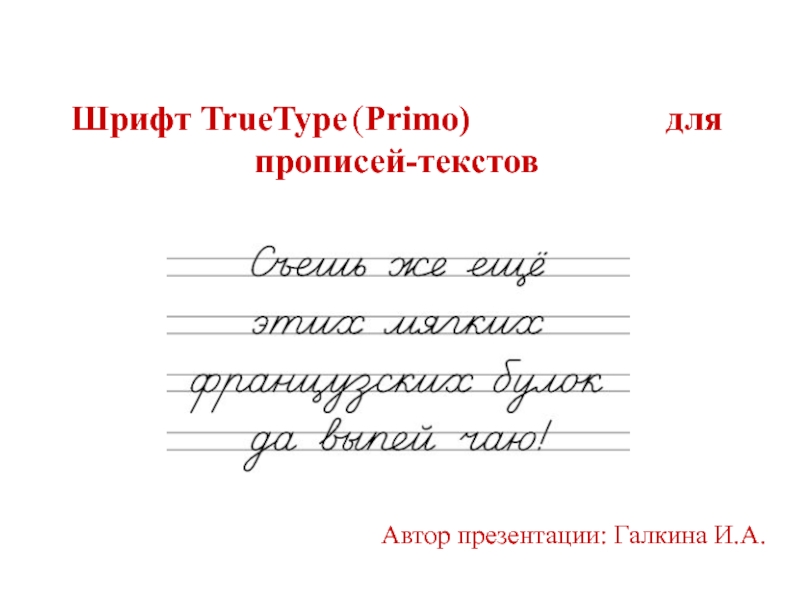
Слайд 1Шрифт TrueType (Primo)
для прописей-текстов
Слайд 5Вначале текст набирается каким-либо обычным шрифтом, например, Times New Roman.
Слайд 6Затем текст выделяется мышью. Команды:
Сервис – Макросы –
ToPrimo – Выполнить
Слайд 7Макрос ToPrimo переводит выделенный текст в шрифт Primo, вставляя при этом
соединительные линии. Можно изменить цвет букв в текстовом редакторе  (например, серый для обводки).